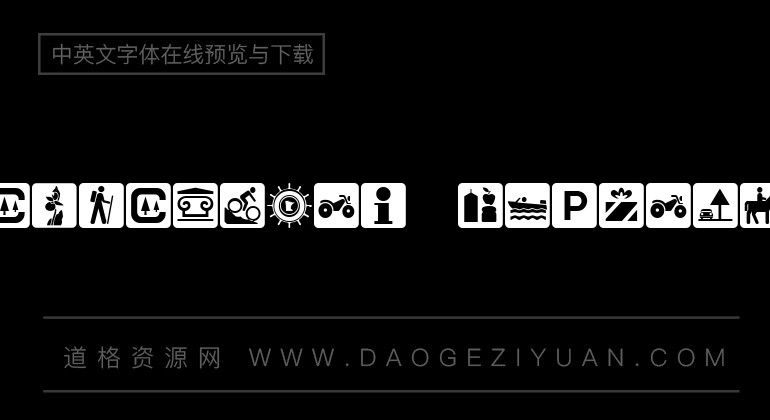
DNR Recreation Symbols Font
DNR Recreation Symbols Font 是一个可扩展的符号字体,旨在提供各种户外休闲活动所需的符号。它由美国密歇根州自然资源部门(Department of Natural Resources,简称DNR)开发,可用于为各种户外休闲活动创建地图和指南。 该字体包括了各种符号,如营地、钓鱼、徒步旅行、步道、野营、狩猎、皮艇、骑马、滑雪、滑雪板、雪鞋、骑自行车、沿海活动、野生动物、森林和湖泊等活动的符号。这些符号可以用于设计地图、指南、方向标志和其他户外休闲活动的相关图形。 该字体是免费提供的,并且可以在Windows和Mac OS X操作系统上使用。它还包括了TrueType格式和OpenType格式,可用于在各种软件程序中使用,如Adobe Illustrator、Photoshop、InDesign、Microsoft Word和Google Docs等。 总的来说,DNR Recreation Symbols Font是一个非常有用的字体,提供了各种户外休闲活动所需的符号,可以帮助设计师和户外休闲活动爱好者更方便地创建地图和指南。